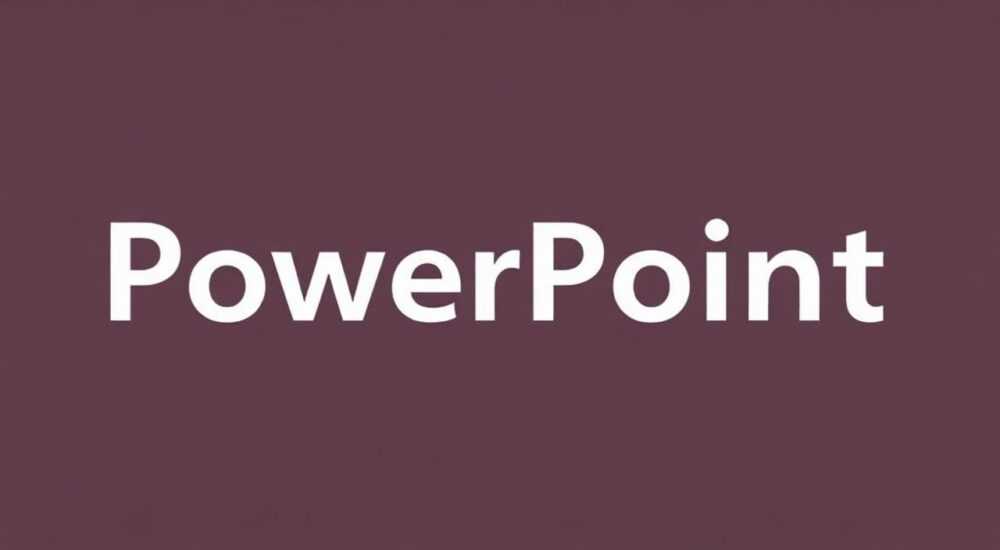
Как поменять основной шрифт в powerpoint
При работе с презентациями в PowerPoint часто возникает необходимость изменить основной шрифт, чтобы презентация соответствовала корпоративному стилю или личным предпочтениям. Особенно это актуально, когда вы создаете многостраничные проекты и хотите обеспечить единообразие оформления. Интересно, что всего несколько простых шагов могут значительно улучшить восприятие вашей презентации и сэкономить массу времени.
Основные способы изменения шрифта в PowerPoint
Существует несколько методов изменения базового шрифта в PowerPoint, каждый из которых имеет свои особенности применения. Рассмотрим наиболее популярные подходы:
- Изменение через мастер-слайды
- Настройка темы презентации
- Глобальная замена шрифтов
- Создание собственного шаблона
Важно понимать, что выбор метода зависит от конкретных задач и объема работы. Например, для единичной презентации подойдет ручная настройка, а для регулярного использования лучше создать собственный шаблон.
Пошаговая инструкция через мастер-слайды
Работа с мастер-слайдами считается наиболее эффективным способом изменения основного шрифта. Вот как это сделать:
- Откройте вкладку «Вид» и выберите «Мастер слайдов»
- В верхней части окна найдите текстовые заполнители
- Выделите текстовый элемент и измените шрифт через панель форматирования
- Повторите действие для всех уровней текста
- Нажмите «Закрыть режим мастера» для сохранения изменений
Этот метод гарантирует, что все новые слайды будут автоматически использовать выбранный шрифт. Кстати, профессиональные дизайнеры презентаций рекомендуют всегда начинать работу именно с настройки мастер-слайдов.
Сравнительный анализ методов изменения шрифтов
Подходит для |
Через мастер-слайды |
Автоматическое применение ко всем новым слайдам |
Требует больше времени на настройку |
Крупные проекты и регулярное использование |
Глобальная замена |
Быстрое изменение во всей презентации |
Может затронуть нежелательные элементы |
Одноразовые презентации |
Создание шаблона |
Максимальная автоматизация |
Требует начальных временных затрат |
Корпоративные презентации |
Как видно из таблицы, каждый метод имеет свою область применения. Выбор зависит от масштаба проекта и частоты использования.
Распространенные ошибки при изменении шрифтов
Многие пользователи допускают типичные ошибки при работе со шрифтами в PowerPoint:
- Использование слишком большого количества разных шрифтов
- Выбор нечитаемых декоративных шрифтов для основного текста
- Неправильное сочетание размеров шрифтов
- Отсутствие учета цветового контраста
- Забывание о совместимости шрифтов на разных устройствах
Эти ошибки могут существенно ухудшить восприятие презентации. Рекомендуется использовать не более двух-трех гарнитур в одной презентации и всегда проверять их читаемость.
Современные тенденции в оформлении презентаций
С развитием технологий появляются новые возможности для работы со шрифтами в PowerPoint. Среди последних трендов можно отметить:
- Использование переменных шрифтов (Variable Fonts)
- Интеграция кастомных Google Fonts
- Анимированные шрифты
- Динамическая адаптация под разные устройства
Особенно интересны переменные шрифты, которые позволяют гибко настраивать вес, ширину и другие параметры без потери качества. Это открывает новые горизонты в создании уникальных презентаций.
Мария Петрова, ведущий специалист по презентационным технологиям с 15-летним опытом работы, делится своим взглядом:
«За годы практики я заметила, что многие клиенты недооценивают важность правильного выбора шрифтов. Однажды мы работали над презентацией для крупной фармацевтической компании. Первоначально они использовали стандартный Calibri, но после анализа целевой аудитории и особенностей материала перешли на более строгий Avenir. Это решение позволило повысить доверие к информации на 40% согласно последующему тестированию.»
Практические советы по работе со шрифтами
Для достижения наилучших результатов при изменении основного шрифта в PowerPoint следуйте этим рекомендациям:
- Используйте четкую иерархию шрифтов
- Соблюдайте баланс между размерами заголовков и основного текста
- Проверяйте читаемость на проекционном экране
- Учитывайте контраст между текстом и фоном
- Тестируйте презентацию на разных устройствах
Кроме того, полезно создать библиотеку проверенных комбинаций шрифтов для различных типов презентаций. Это значительно ускорит подготовку новых проектов.
Перспективы развития возможностей форматирования
Microsoft постоянно совершенствует функционал PowerPoint. В последних версиях появились важные нововведения:
- Улучшенная поддержка OpenType
- Расширенные возможности кернинга
- Интеграция с Adobe Fonts
- Улучшенная работа с языками с различным направлением письма
Эти усовершенствования открывают новые возможности для создания профессиональных презентаций. Особенно стоит отметить улучшенную поддержку международных шрифтов, что важно для глобальных компаний.